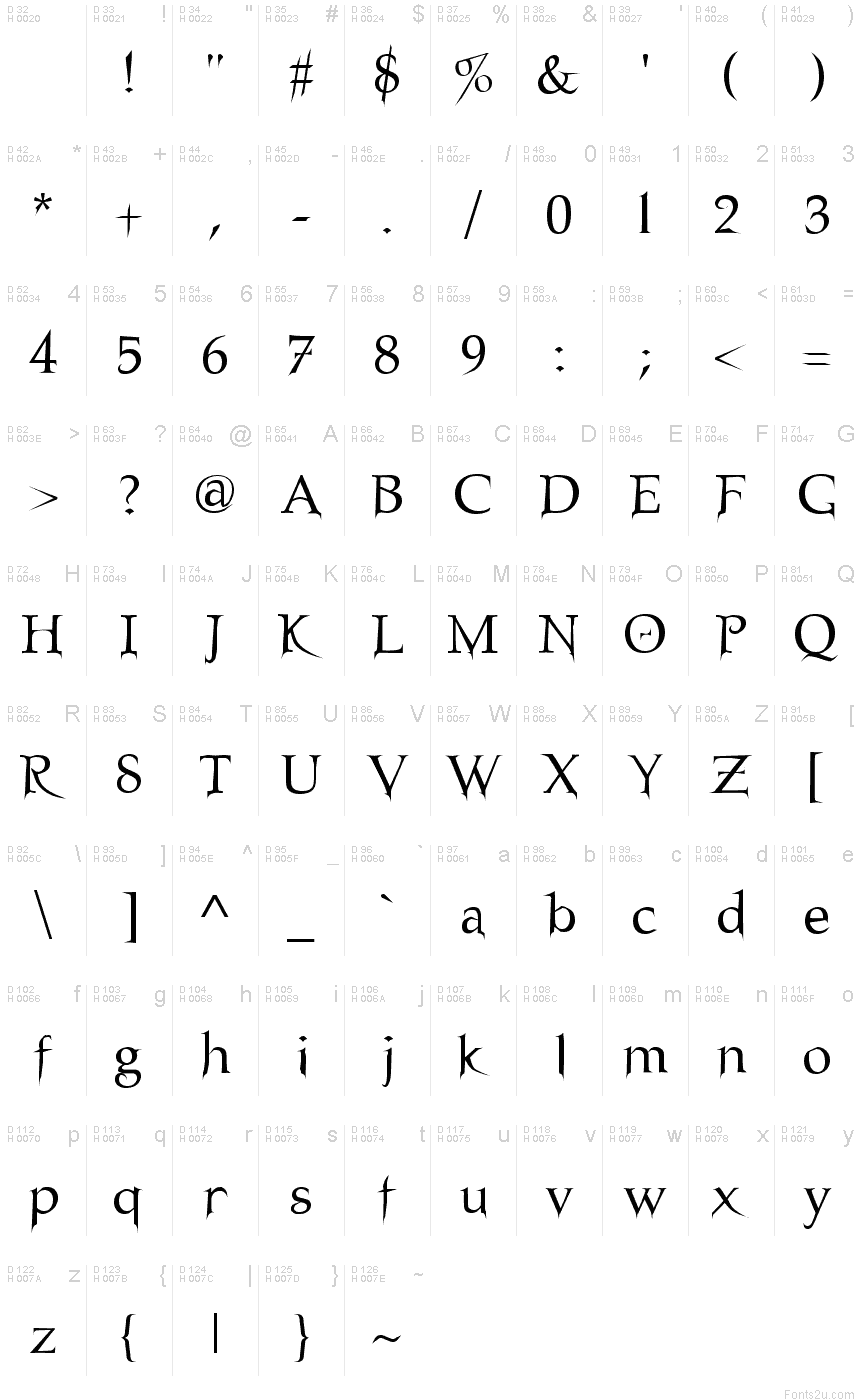
Nosfer di Eric Oehler è un font display gratuito dal carattere horror, con tagli serif affilati, tratti sottili e terminazioni appuntite e irregolari che conferiscono alle lettere un aspetto intagliato e spettrale. Le forme appaiono essenziali e tese, con alcuni discendenti lunghi e affilati come lame che rendono questo carattere più adatto ai titoli che al testo corrente.
Nosfer è perfetto per locandine horror, inviti per Halloween, copertine di libri, titoli e loghi a tema, dove quei dettagli frastagliati riescono a trasmettere l'atmosfera all'istante. Questo font gratuito funziona bene anche per volantini di eventi e intestazioni decorative, quando vuoi che il testo appaia inquietante senza risultare troppo elaborato.